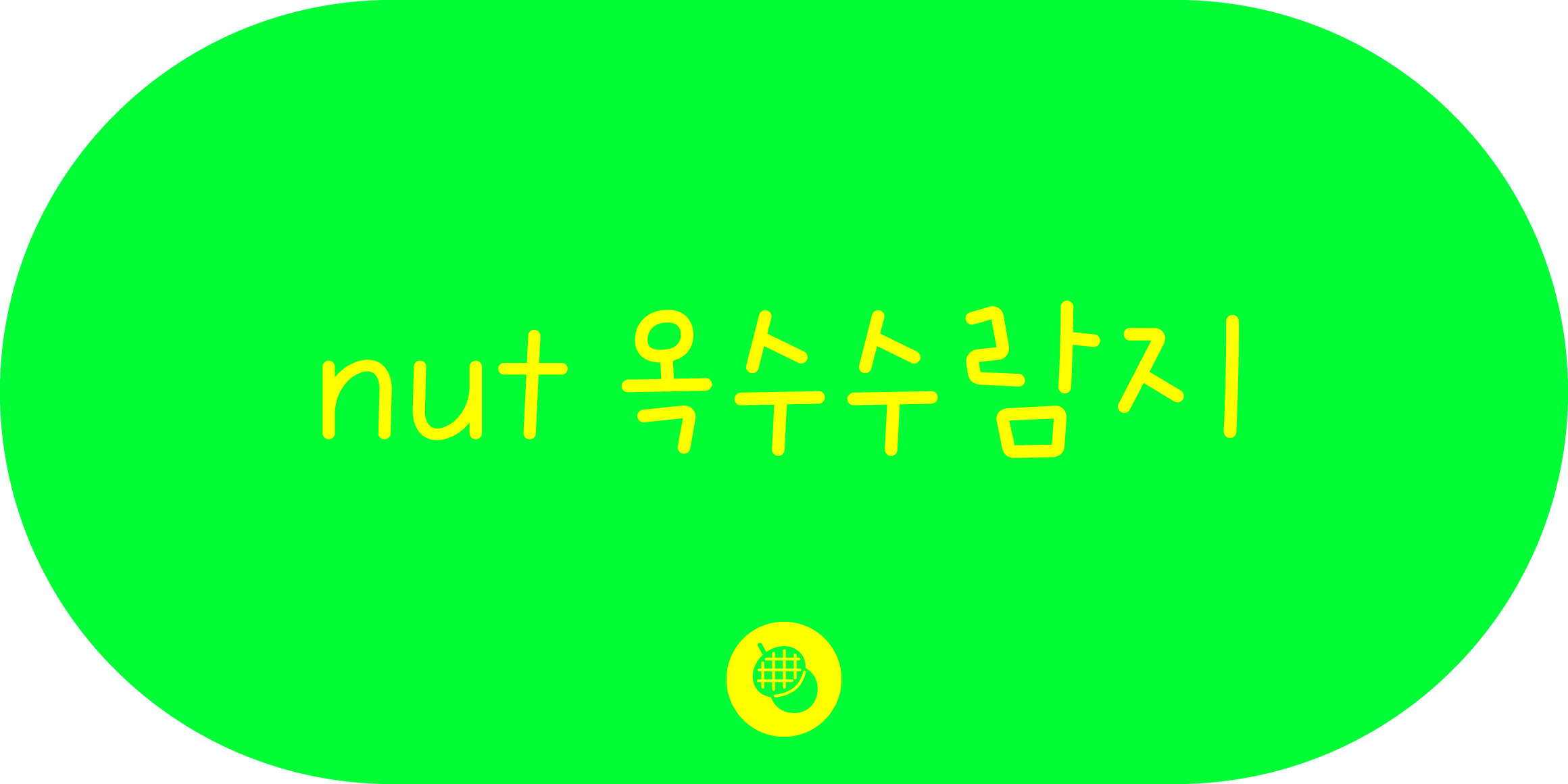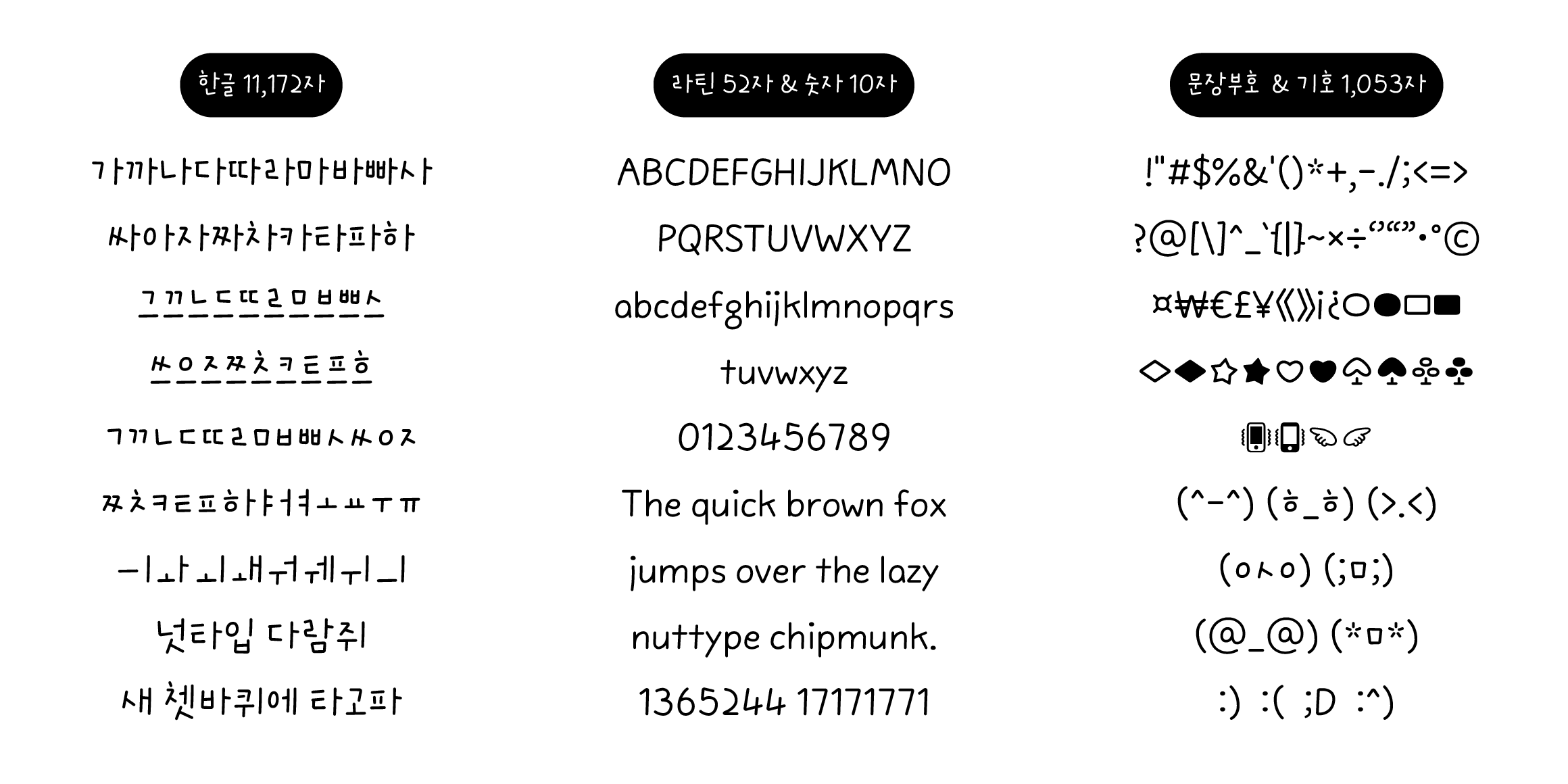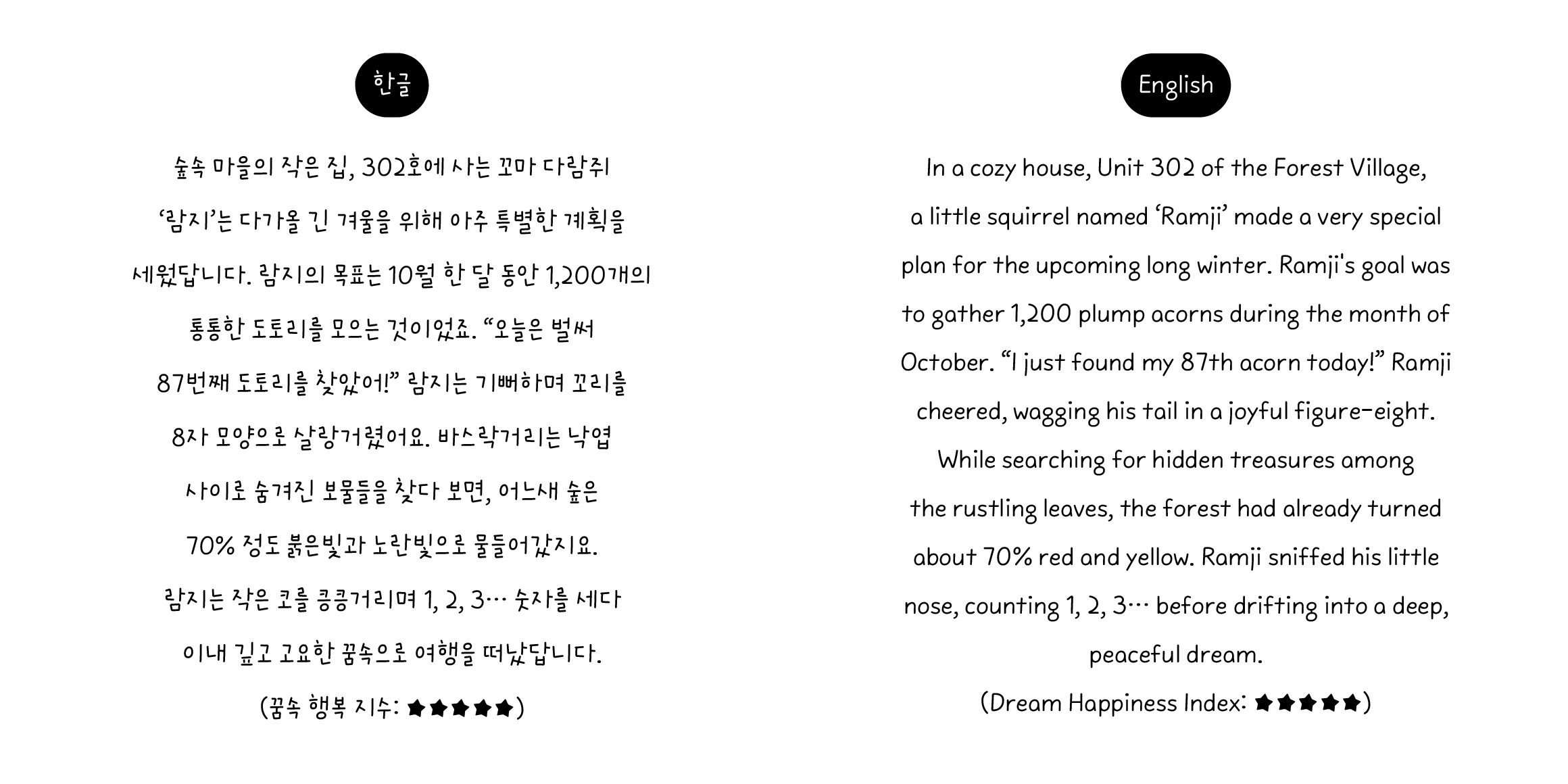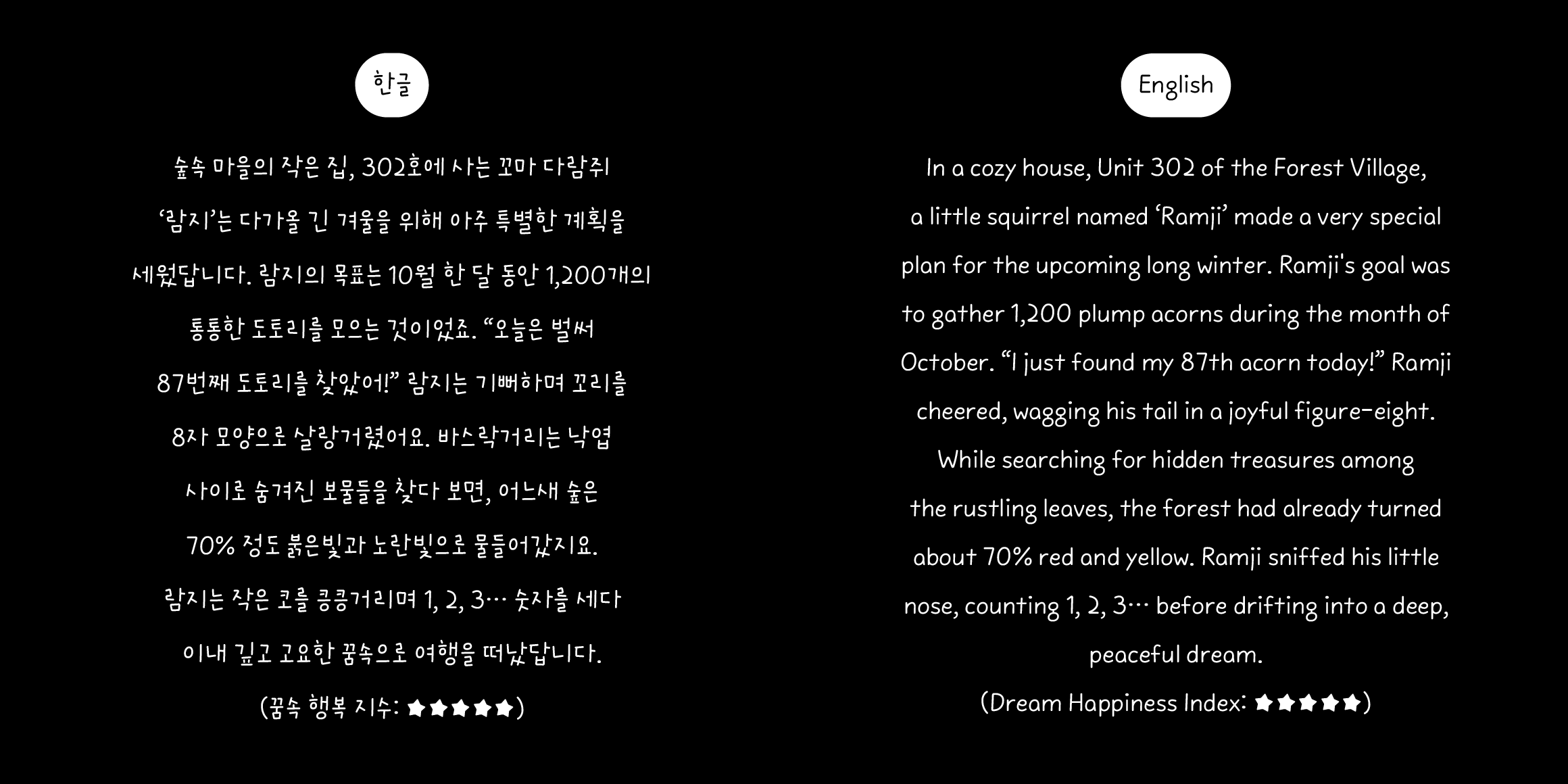
nut 옥수수람지
Nuttype
분류 Script,손글씨
나는 옥수수람지다. 그리고 나는 오늘도 쫄깃하다. 이 말은 생각보다 대단한 말이다. 세상에는 바삭한 것도 많고, 부드러운 것도 많고, 입에 넣자마자 사라지는 것도 많다. 하지만 옥수수는 다르다. 한 번 씹는다고 끝나지 않는다. 한 번 더 씹어야 하고, 또 한 번 씹어야 한다. 그리고 그때마다 톡, 톡, 톡. 알 하나하나가 이를 밀어내면서 자기 존재를 주장한다. 나는 옥수수람지. 노랗고, 고소하고, 달콤하고, 무엇보다— 쫄깃하다. 그리고 이 세상에서 쫄깃하다는 건 꽤 괜찮은 일이다.
• nut 옥수수람지 / nut Oksusu Ramji